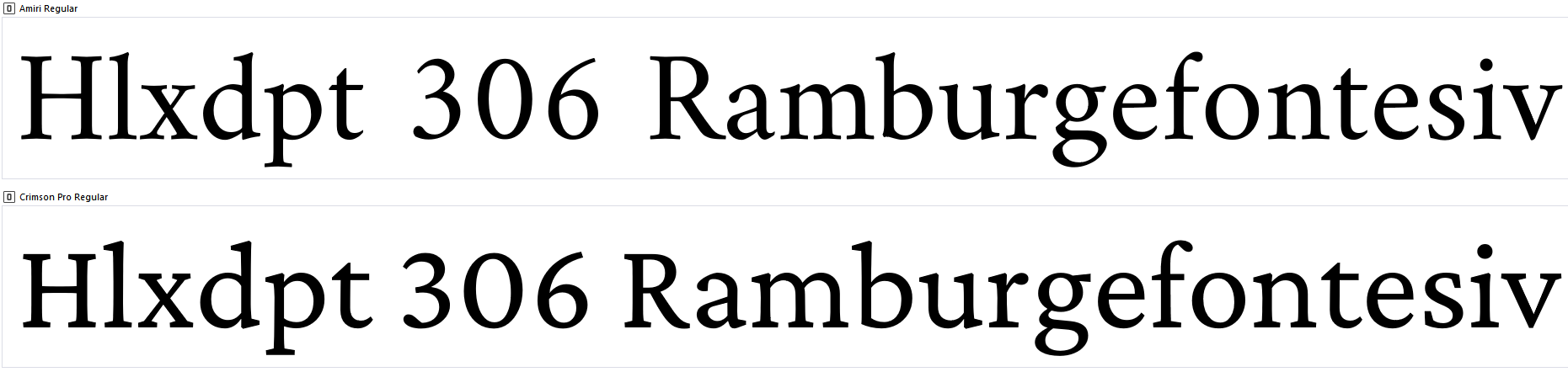
Gesucht: Font für Mengentext in lateinischer Schrift, vollständige diakritische Zeichen, Griechisch, Hebräisch, Arabisch, Äthiopisch
Und du kannst zwischen Sans und Serif wählen.
Schon beeindruckend, was da inzwischen alles entstanden ist – eine frei verfügbare Antiqua in drei Weiten! Das findet man ja schon bei den kommerziellen Fonts kaum. :-o
Ich stelle mich gerade auch einer Herausforderung mit diakritischen Zeichen, mit dem Unterschied, dass sie sich »nur« auf ein paar Namen in einer Publikation beschränkt. Der Text ist aus der Univers gesetzt und ich will nachvollziehbar deswegen nicht das typografische Konzept umwerfen. Bleibt mir also nur, die Zeichen selbst unter Zuhilfenahme der Glyphen zu »bauen«, vielmehr zu justieren.
PS: Erst gab es diese Herausforderung gar nicht, doch nachdem eine diversitätssensible Korrektur stattgefunden hat, wurde Reza Abbasi zu ʾĀqā Riḍā ʿAbbāsī als ein Beispiel.
Den Punkt und die Breven muss ich noch modifizieren / exakter und homogener platzieren. Letztere sind gekippt, da sie in den Glyphen so nicht vorhanden sind…
Ist das islamwissenschaftlich (o.ä.) oder semitistisch? Bei islamwissenschaftlichen  Publikationen kann sonst auch das anlautende Hamza vor ʾĀqā in der Umschrift wegfallen, also Āqā.
Nachbauen wie von Dir beschrieben funktioniert aber nur, wenn Du tatsächlich der Endpunkt der Bearbeitung bist, sonst zerschießt es u.U. woanders diese Baukasten-Buchstaben.
Schwer zu beurteilen, da es bei diesen Transliterationen eben kein festes Regelwerk zu geben scheint (»… wird ein Hamza am Wortbeginn in vielen Umschriften nicht wiedergegeben.«) Also wohl eher semitistisch?
Richtig, oder man brieft entsprechend genau. Würde man generell die Laufweite modifizieren (sollte in dieser Phase natürlich nicht mehr stattfinden, aber als Beispiel), gäbe es ein böses Erwachen aufgrund der Unterschneidungen. Um dem entgegenzuwirken, könnte man den konstruierten Buchstaben in Pfade umwandeln und ihn an die Position im Textfeld kopieren. Nur muss dann wiederum in dem Fall das »ḍ« der Schriftlinie angeglichen werden.
So oder so – es bleibt etwas umständlich.
Edit: Anscheinend gibt es auch ein Script, um solche neu konstruierten Zeichen dem Glyphensatz hinzuzufügen, nur existiert nach Recherche der entsprechende Link nicht mehr.
Das ist mir dann aber doch zu kompliziert, glaube ich…
Die Crimson Pro wurde nochmal anders entwickelt:
The first Crimson design was initiated by Sebastian Kosch in 2009, and he later completely redrew a new version called Crimson Prime. Google commissioned Jacques Le Bailly to review both typefaces, and develop Crimson Pro as a new design that synthesises both designs into a final authoritative family [...]
Alles etwas unübersichtlich, zumal das nicht die einzigen Crimson-Derivate sind. Das soll mal noch einer nachhalten...